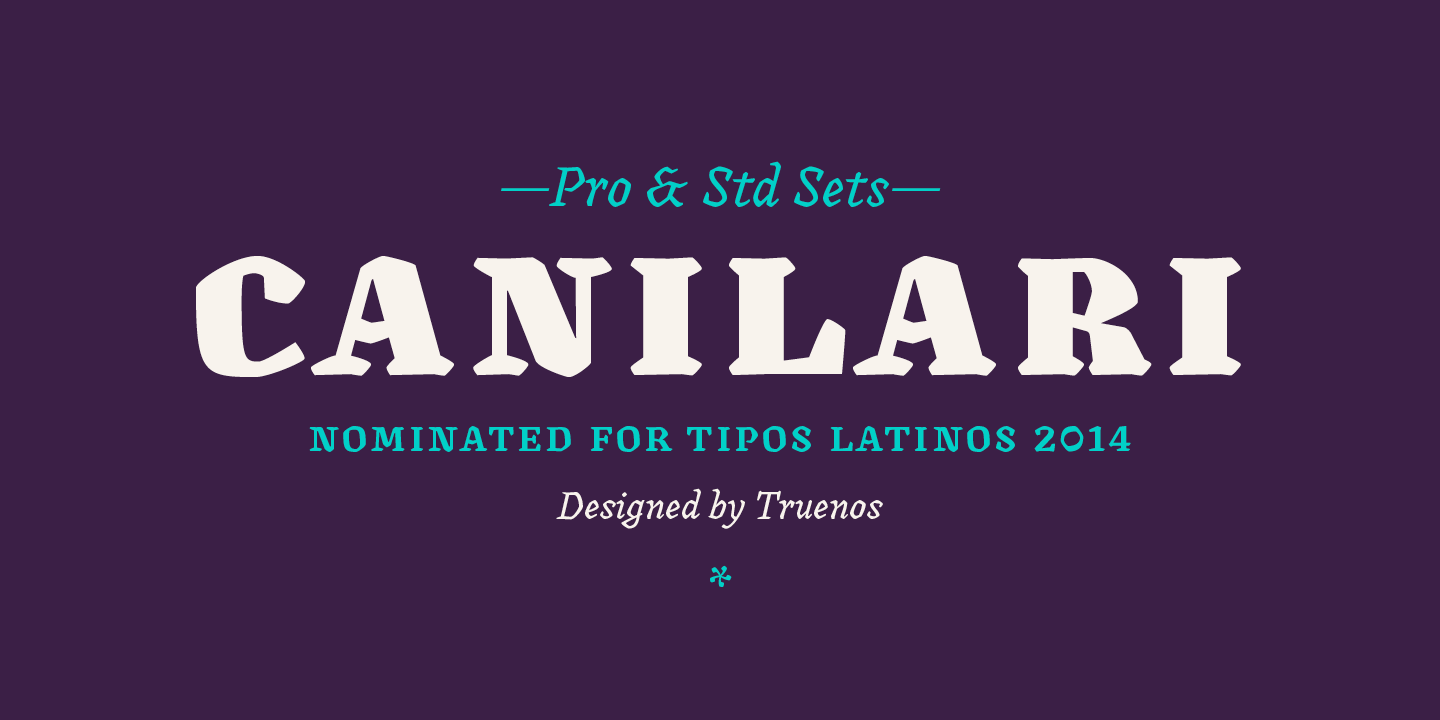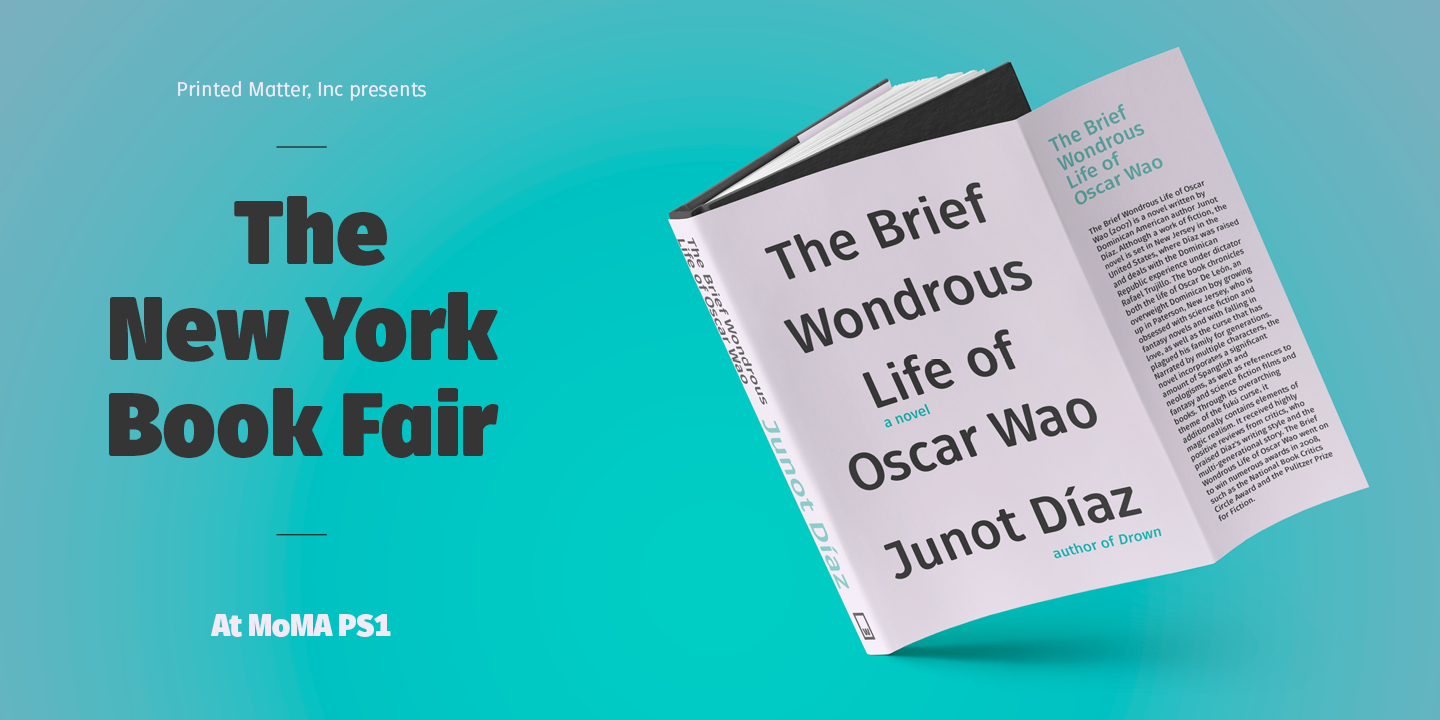
Die Petala Pro, eine Grotesk-Familie mit 9 Strichstärken, jeweils normal und kursiv, ist zur Zeit im Sonderangebot:
Die Schnitte sind alle sehr umfangreich ausgebaut mit Kapitälchen und Versal-Eszett (auch in den Kapitälchen) sowie jeder Menge Ligaturen wie ffy, fh, fk, ffb usw..
Ja, an der bin zunächst auch hängen geblieben, aber nach genauerm Hinsehen fand ich sie dann doch eher unausgegoren und Fonts wie FF Amman Serif oder Fakir deutlich überzeugender … also spare ich lieber weiter.
Zu FUSE V.2:  Habe die Pakete mal gekauft u. festgestellt, daß beim TEXT Package unter WORD keine Tabularziffern einstellbar sind. Nach den Glyphen müßten die drin sein - sehr ärgerlich.
Oder irre ich mich?
Also nach der MyFonts-Vorschau verfügen dieText-Schnitte nur über Mediävalziffern, die aber sowohl in (standardmäßig aktiven) Proportional- als auch  (per Opentype aktivierbaren) Tabularversionen. (Die korrespondierenden Versalziffern gibt’s dann nur in den Displayschnitten.)
Wenn sich dicktengleiche Mediävalziffern in den Textschnitten nicht aktivieren lassen, liegt das mglw. an Word, würde ich mal vermuten.
Also, mit WORD hatte ich bei OTF-Fonts noch nie solche Probleme - inakzeptabel ist das. Mal hören, was von Myfonts dazu kommt.
Wie findet ihr die so? Klar, es soll irgendwie handgemacht aussehen, aber kommt das für euch auch rüber – oder sieht es einfach nur krumm und schief aus? Ich kann mich gerade nicht so recht entscheiden … :-?
In der MyFonts-Vorschau stach mir gerade dieses Beispiel ins Auge:
… und dann die Ausschnitte (bewusst?) krumm und schief hinlegt?
Wirkung der Schrift? Auf mich? Also die verschiedenen Winkel der Senkrechten (haha) machen die Schrift vermutlich sehr schwer nutzbar. Wie viele Buchstabenkombinationen gibt es wohl, bei denen das mit den tanzenden Neigungsgraden hinhaut? Ich wüsste gar nicht, wie ich diese Schrift einsetzen sollte – außer vielleicht bei einem Logo. Und da würde ich sie dann auch wieder nicht verwenden, weil ich solche Unregelmäßigkeiten dann eher selber und bewusst gestalten wollen würde. Hinzu kommt, dass mir die Buchstabenformen ein bisschen zu zickig rüberkommen. Das kleine kursive z zum Beispiel kuckt so entrüstet wie Alf, wenn er damals™ in den guten alten Zeiten™ gefragt wurde, ob er die Katze gefressen hat … ;-)
Ok. Also ich als Nicht-Kollege, aber ambitionierter Amateur würde sagen: Je länger ich mir die Schrift anschaue, desto mehr finde ich viele Eigenheiten unpassend und störend und desto weniger gefällt sie mir.
findest Du übrigens, dass die Schrift so aussieht?
Nein, wie aus Papier geschnitten sieht sie nicht aus. Ich habe das nur zitiert, um zu unterstreichen, dass die Schrift tatsächlich absichtlich irgendwie verquer aussehen soll, aber ich hätte wohl einschränken sollen, dass die MyFonts-Beschreibung trotzdem oder auch daneben ist.
… Ich habe das nur zitiert, um zu unterstreichen, dass die Schrift tatsächlich absichtlich irgendwie verquer aussehen soll, …
:nicken: Interessant ist ja, dass die die Schrift überhaupt so beschreiben … :-) Aber das kennt man ja auch von Logos. Da kündigt dann der Gestalter oder die für den Entwurf verantwortliche Agentur das eigene Werk derart blumig und von Bedeutung geradezu überfrachtet an, dass man bei der feierlichen Enthüllung des Logos gar nicht anders kann, als nach Kräften enttäuscht zu sein. ;-)
Ups, das mit den Kollegen ist völlig falsch raus gekommen, sorry. :aschehaupt:
Ich wollte dich, Dieter, jedenfalls keineswegs aus dem Kreis der Kollegen ausschließen, sondern war nur neugierig, wie die Schrift (ungeachtet des zitierten Werbetextes) auf uns alle wirkt.
Aber bei Cutfonts bin ich dabei. Tolle Idee! Das müssten wir aber richtig organisieren, sonst haben wir am Ende 23 ẞs und kein einziges l.
Ach, ich sehe übrigens gerade, dass die ungarischen Diakritika mal wieder unbrauchbar sind und die Familie keinerlei Opentype-Varianten (und damit nur einen – versalen – Ziffernsatz) hat. Das mag bei Einschnitt-Dekoschriften ja OK sein, aber von kommerziellen 10-Schnitt-Sans-Familien erwarte ich heute einfach mehr. Für eine Familie, die ich sehr wahrscheinlich nie einsetzen würde, sind dann selbst $19,80 zu viel. :-(
Und wenn ich mal ein Logo mit Ausschneide-Optik brauche, kann ich ja selbst zur Schere greifen. :cheer: